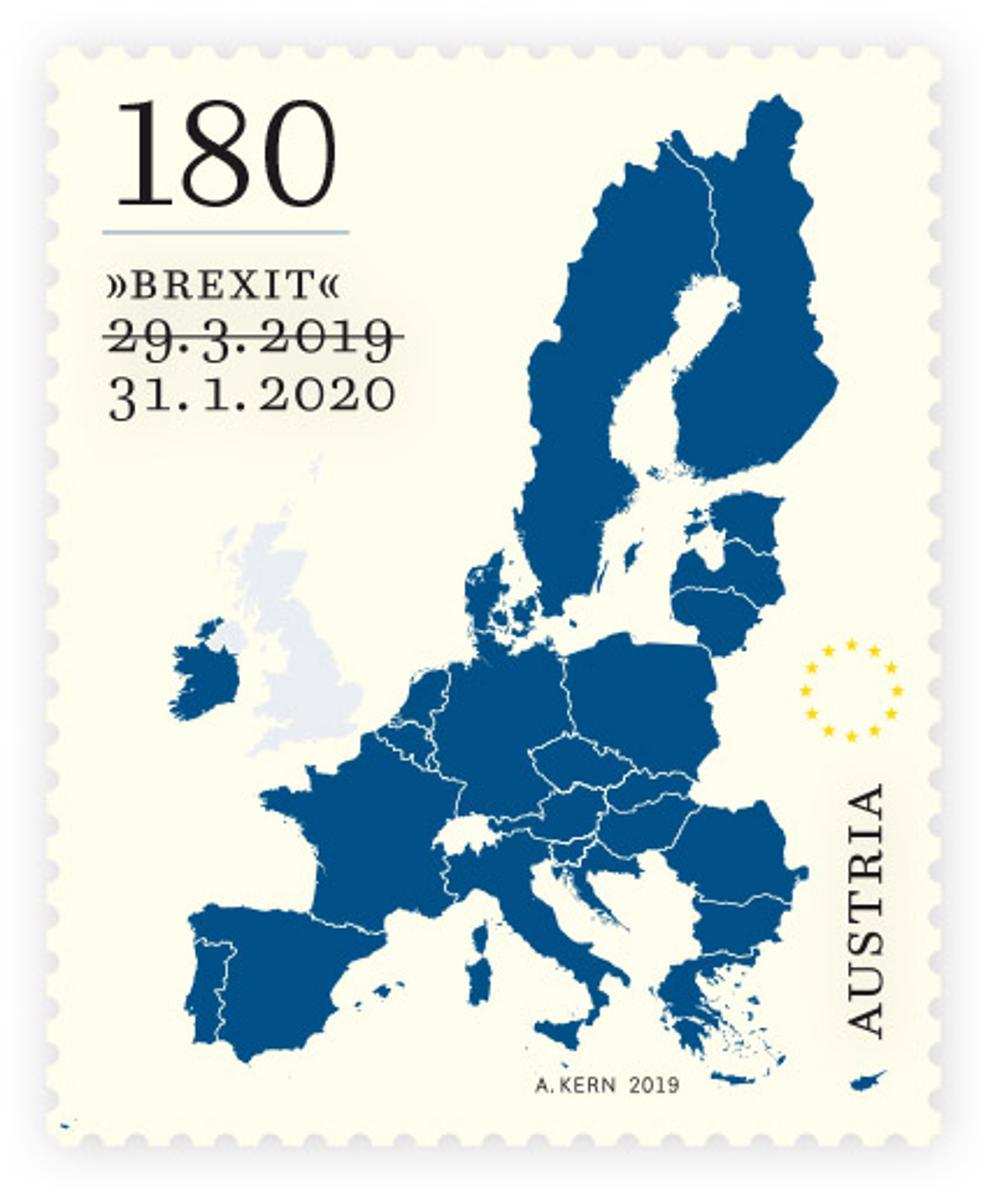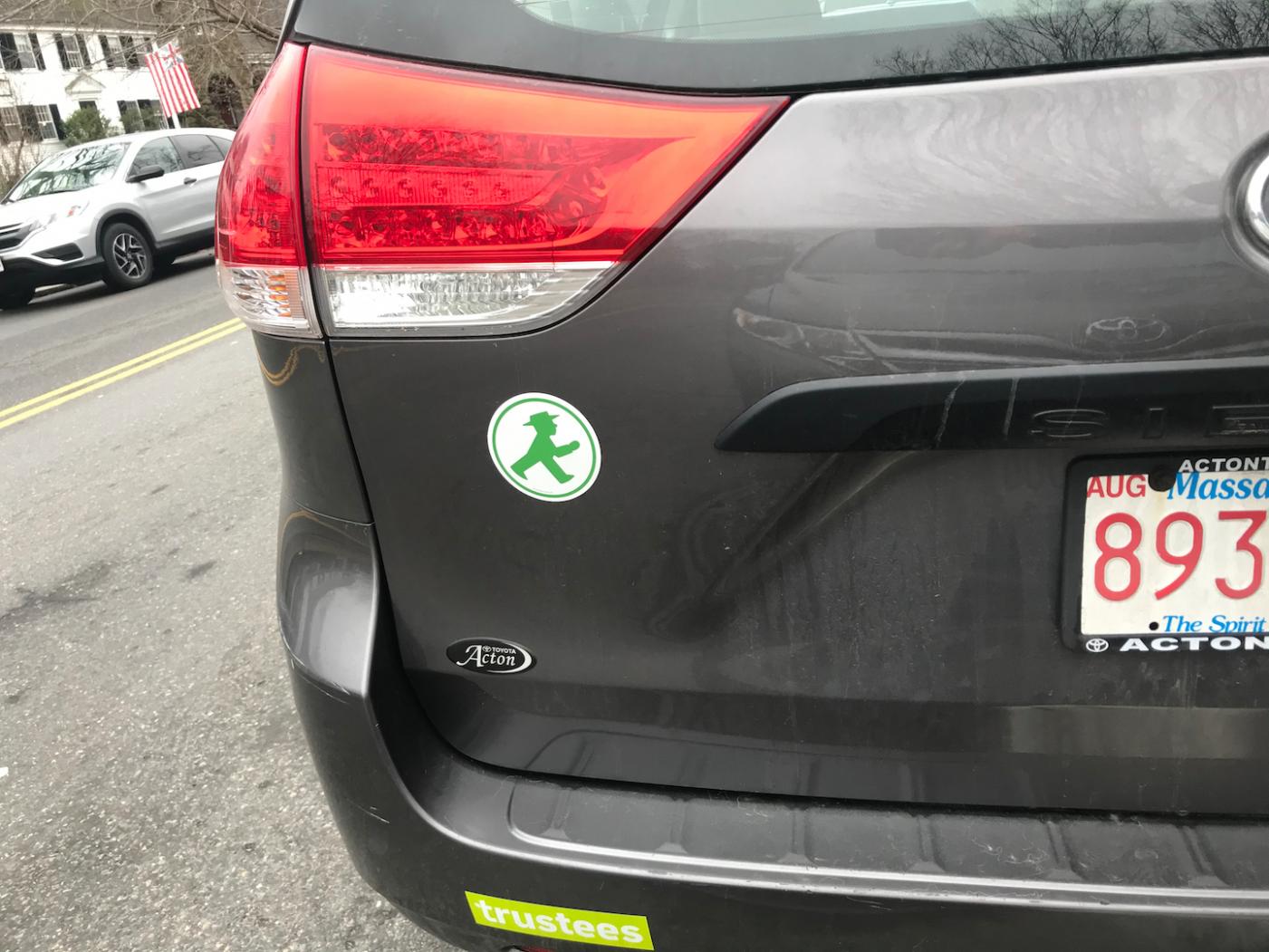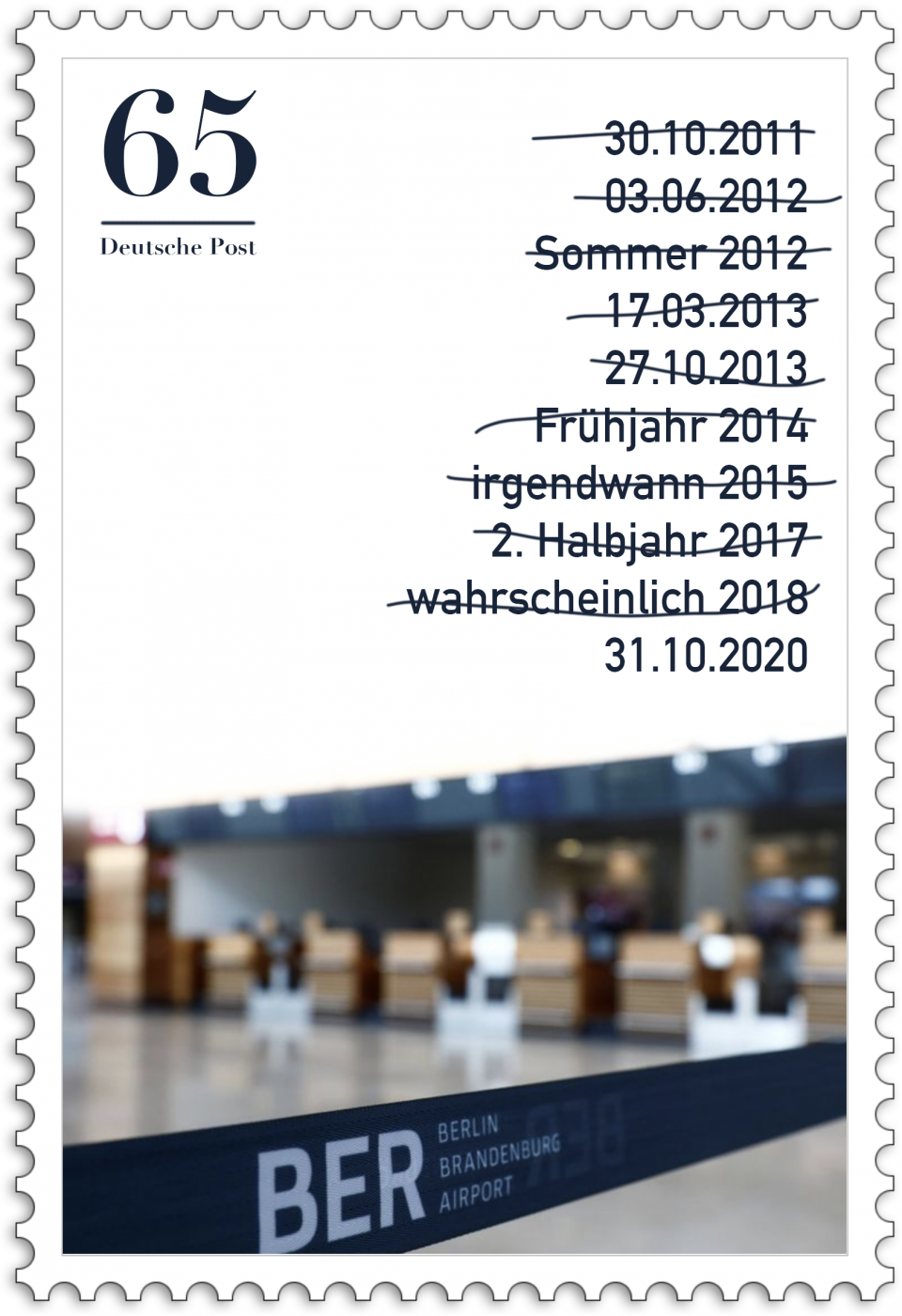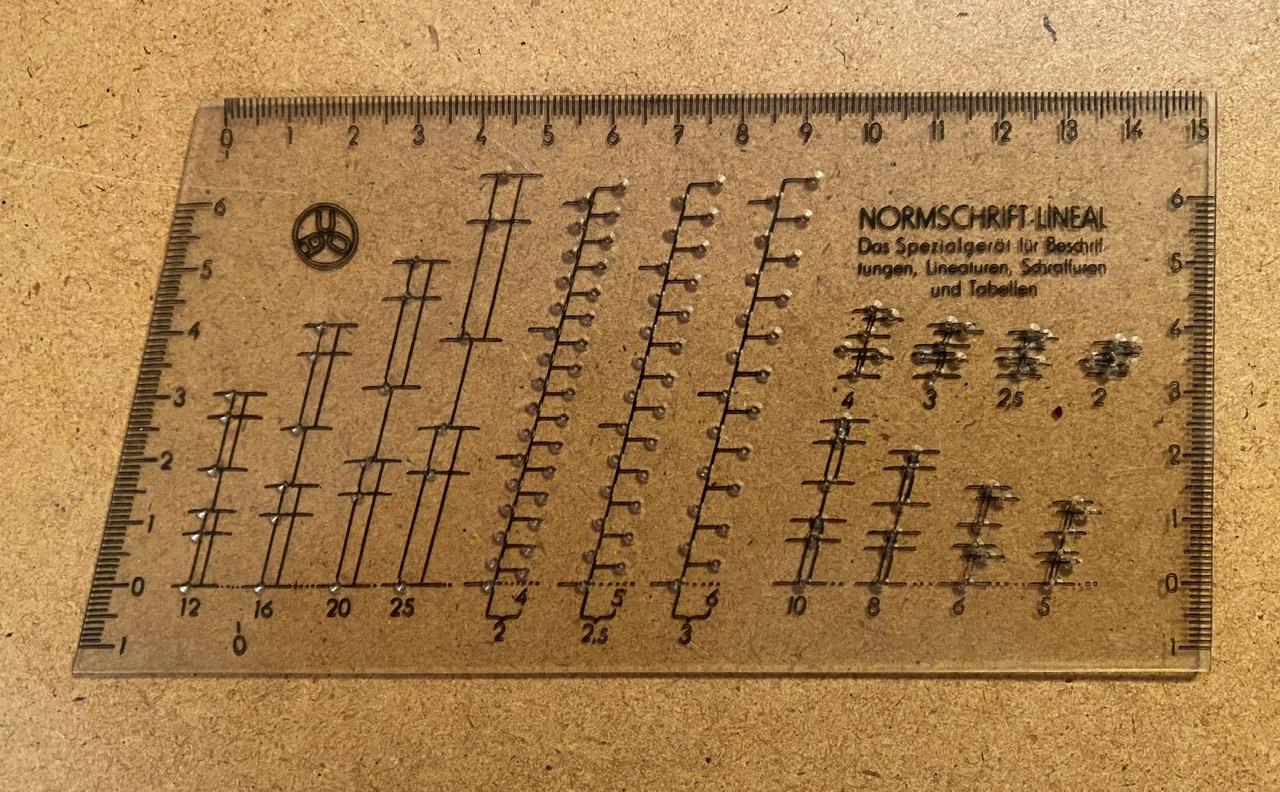
„Die Briefmarken waren schon gedruckt, aber noch nicht im Verkauf“, erklärte Post-Sprecher Michael Homola am Freitag die Entstehungsgeschichte. „Wegwerfen wäre zu schade gewesen. Und dann kam die Idee auf, sie einfach mit dem neuen Datum zu überdrucken." schreibt der Münchner Merkur über die österreichische Post.
Eine großartige Idee, ich liebe den Pragmatismus :biglove:!
So wäre das dann bei uns …
Bist Du sicher, dass diese Marke ausreichend hoch gestaltet wurde? 😉
Nicht gerade typografisch, aber trotzdem ein kurioses Fundstück hier in Lexington, Massachusetts. Recht wenige Leute hier werden wissen, was es mit dem grünen Männchen auf sich hat.
Heute ist Datums-Palindrom:
02.02.2020
Darauf hab ich jetzt fast 900 Jahre gewartet … 11.11.1111 war das letzte Mal.
Ja, ja, mit zunehmenden Alter lassen die Rechenleistungen nach ...
Gut 900 oder fast 909!
Und schläfrig wird man auch im hohen Alter, denn den 20.02.2002 haste wohl verpennt ... ;-)
da war ich wohl krank … :-| nee, ich hab vergessen "weltweit" anzugeben, es muss also Montag* und Tag vertauscht werden können.
*Das soll natürlich Monat heißen. :shock:
Den Montag könnte ich jederzeit gerne eintauschen, schönen selbigen noch ;-)
Dir auch einen schönen Monat :-D.
Ach, wie schön! Bei mir 🇩‍🇪 oder meinen Eltern liegt noch so ein Teil herum. Aber ohne Anleitung, so dass ich nie richtig wusste, wie ich es benutzen sollte. Danke sehr! Þorstelinchen wird im Sommer fleißig linieren.
Das kam mir gerade bei meinen Jugendstil-Recherchen unter. Das Ä macht mir feuchte Hände.
Gilt das noch als Umlaut oder nicht schon eher als Ligatur?
(Ach, wie gern würde ich so etwas einbauen dürfen in manche Texte. Wie oft taucht da etwa die Zeitschrift Aethiopica auf ...)
Naja, das kommt ja wohl aus einer Zeit als die Uebergänge noch fließend waren:
Da wäre die Frage eher: Gilt das schon als Umlaut oder nicht noch als Ligatur ;-)